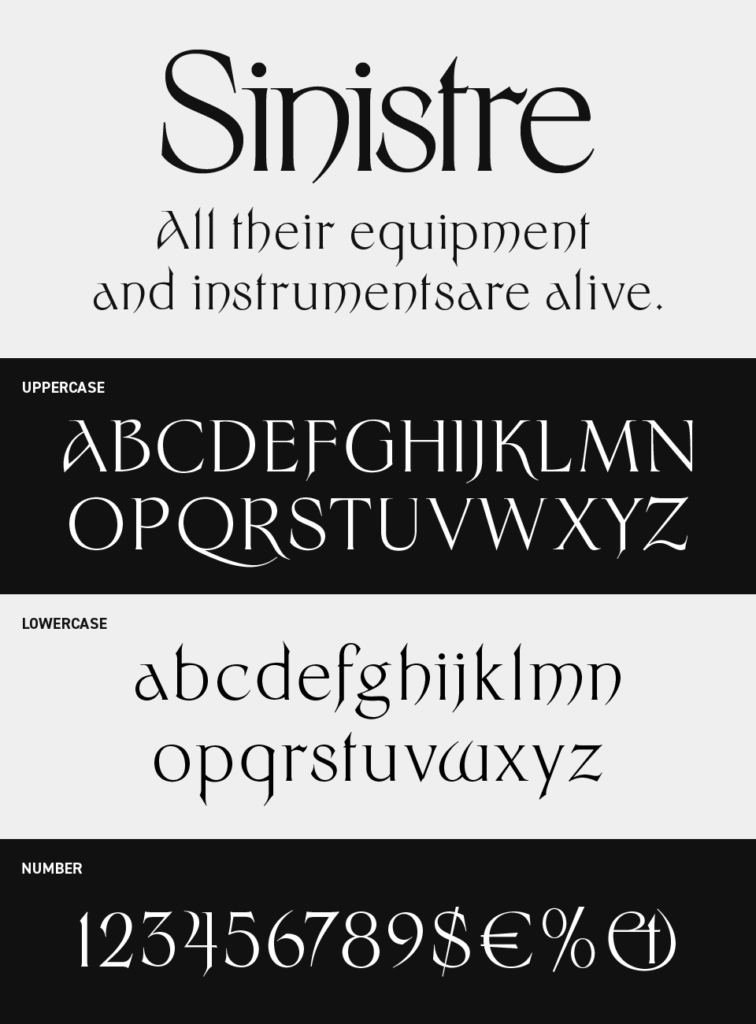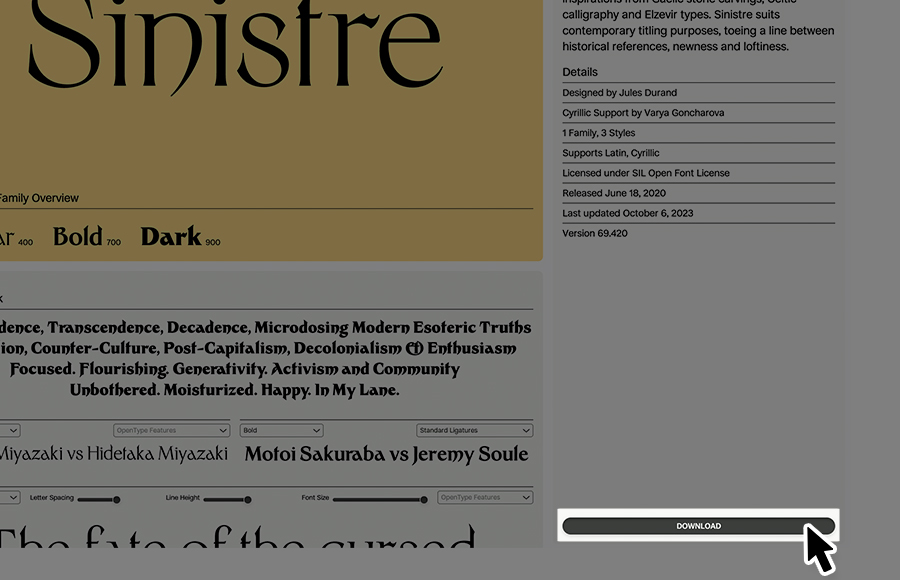
Sinistreフォントは、細身で鋭いエッジを持つファンタジー感のあるデザインフォントです。
縦長のプロポーションと繊細なラインが、紙面に静かな緊張感を生み出すフォントです。高級感のある雰囲気をまとい、魔法や剣・杖などのモチーフにも見えるので、ファンタジー感の雰囲気のビジュアルとも相性が良いです。
字形の流れに独特のクセがあり、文字を並べるだけで雰囲気のある世界観が立ち上がるフォントです。